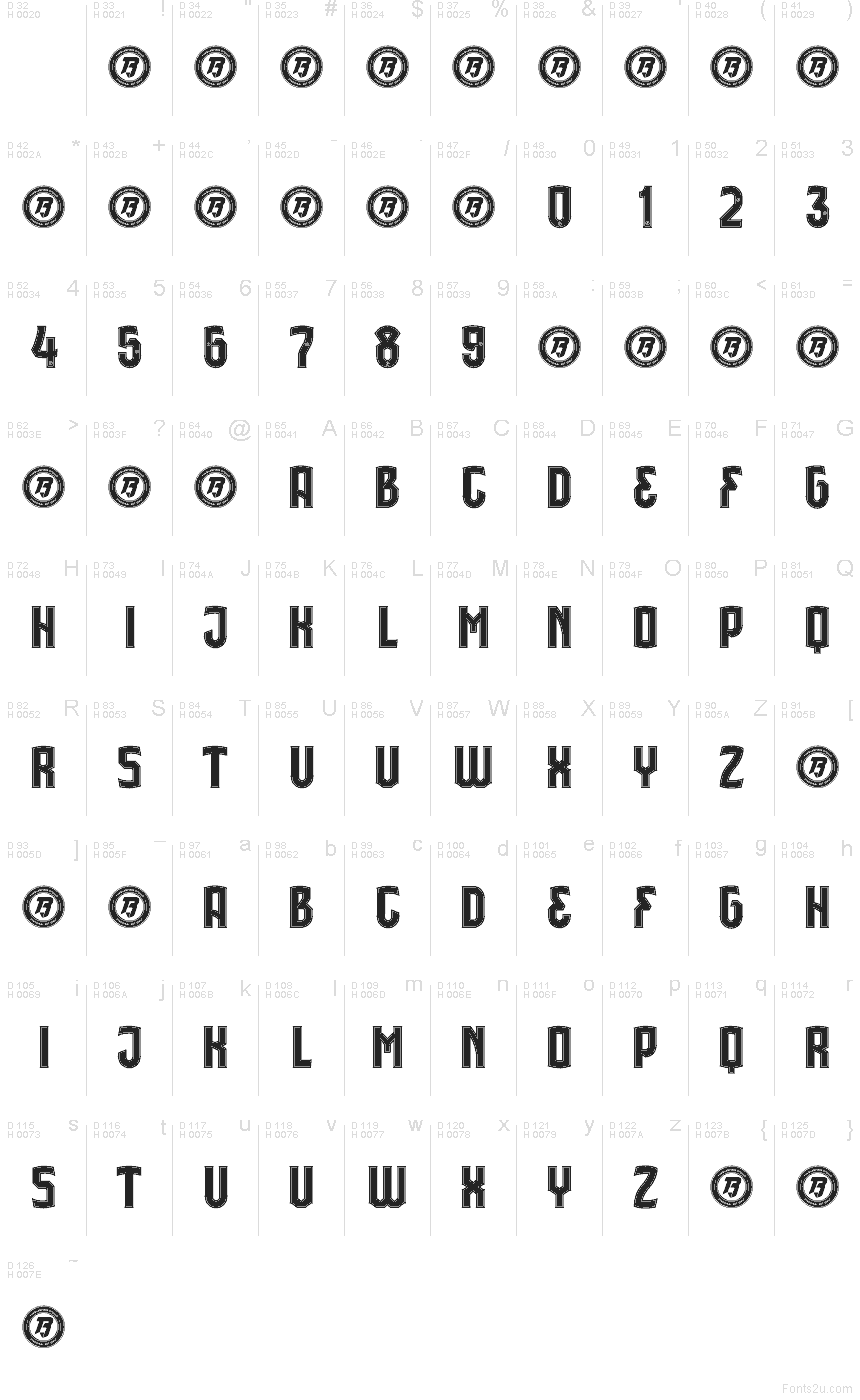
Lombardy, do Trequartista Studio, é uma fonte vintage gratuita estilo cartaz, com letras altas e robustas, linhas internas e uma silhueta que remete à tipografia de madeira. Suas maiúsculas passam um ar teatral e clássico em vez de ornamentado, com traços largos e junções chanfradas que dão ao texto uma presença sólida, como a de um outdoor.
É perfeita para cartazes, embalagens, letreiros, branding de eventos, capas e títulos onde você precise daquele estilo autêntico, entre a feira e a rua principal. Como fonte gratuita, a Lombardy é especialmente útil para logotipos, monogramas e letras capitais, pois o detalhe em linha integrado dá peso visual suficiente até mesmo a poucas letras para sustentar um design.